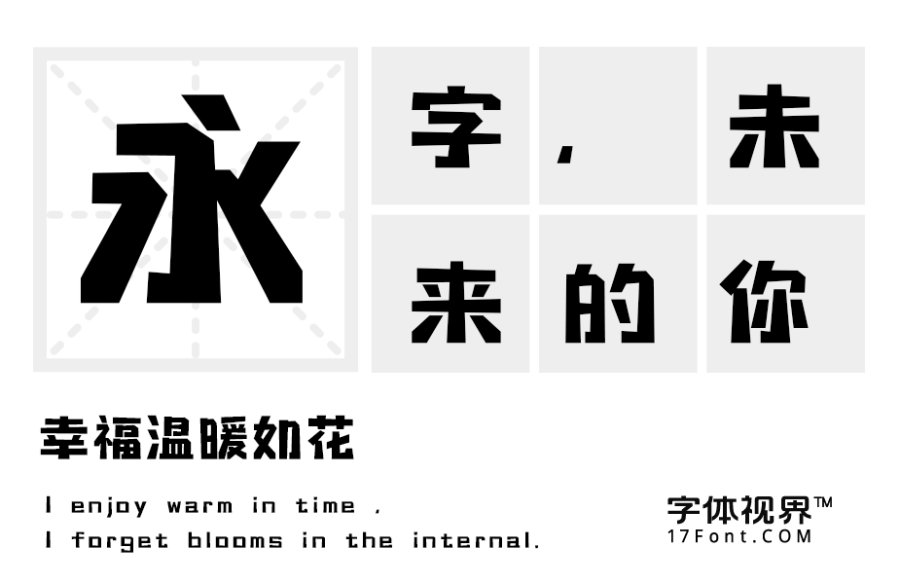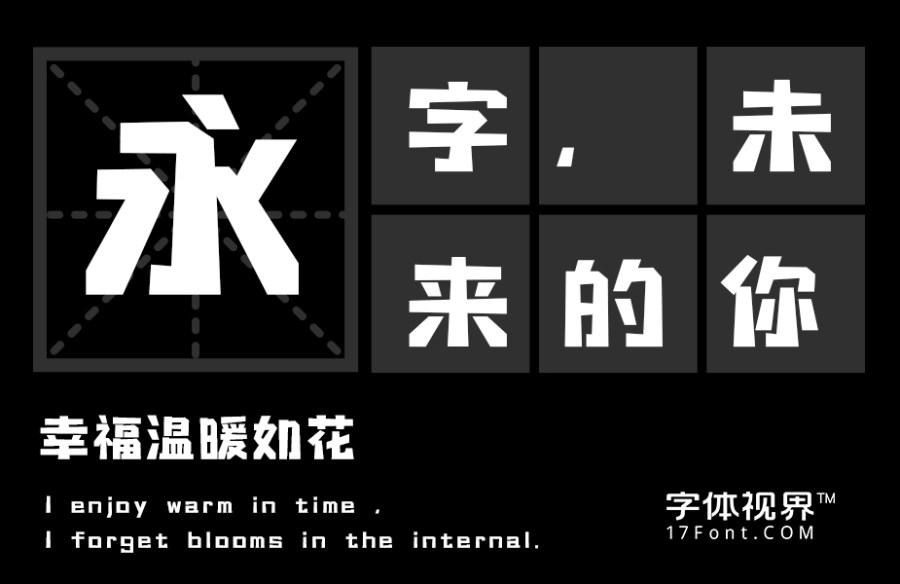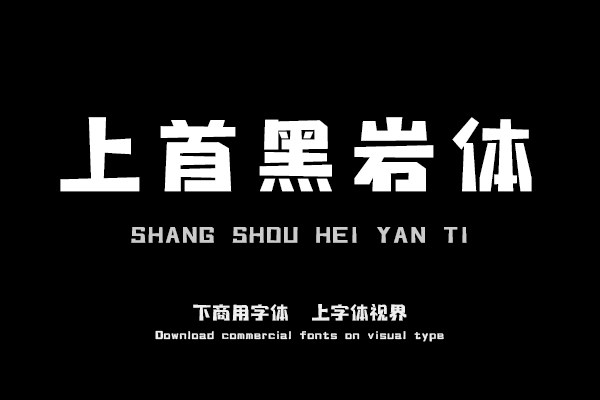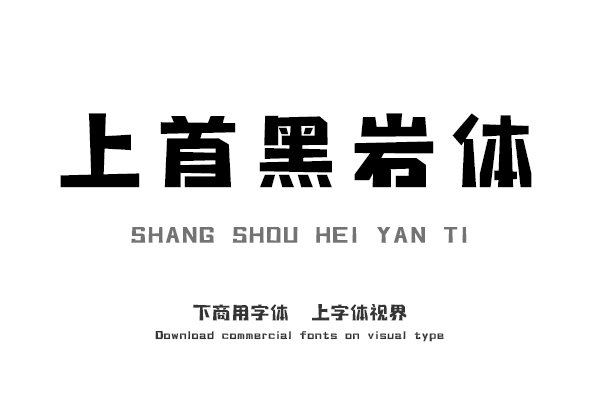
上首黑岩体,字体笔画稳重,形似黑岩,横竖笔粗细变化让人感受到山岩的厚重。适用于搭配标志、广告标语、商业广告等高端属性。购买须知:“下载服务费”与“字体VIP”所获得字体 仅用于个人非商用, 商用请联系付费授权。本字体为电脑用字,手机没有root权限不支持直接手机换字(手机如何root,请自行百度搜索教程)。购买前请先 了解清楚后再付款 ,字体为虚拟产品无法回收 一旦购买不支持退款。